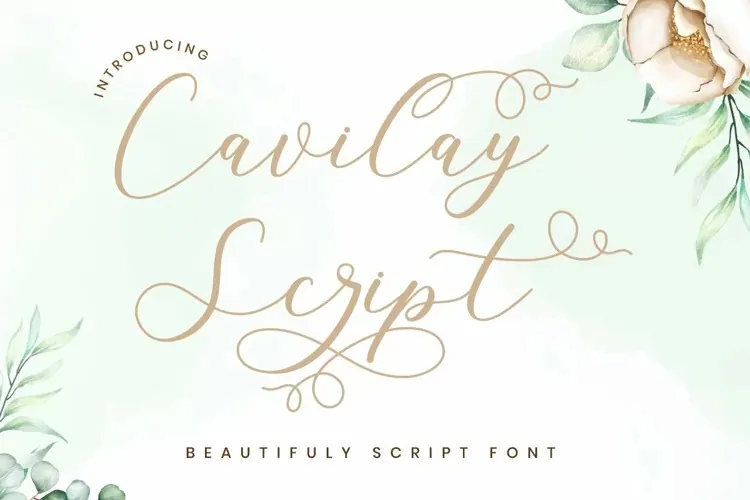
Esta fonte é uma criação moderna do calligrafia, incluindo variante Regular. Ela se destaca por ser casual e encantadora com a presença de swash, características que complementam perfeitamente a elegância e sofisticação. Cavilay Script é ideal para eventos casuais como bodas, aniversários e festas de aniversário, bem como cartões de cumprimentos e logomarcas. Essa fonte também se adequa à criação de logotipos, embalagens de papelaria e até mesmo páginas web ou materiais promocionais que buscam uma sensação de escrita manual e sofisticação. Com Cavilay Script, suas produções ganham um toque elegante e único.